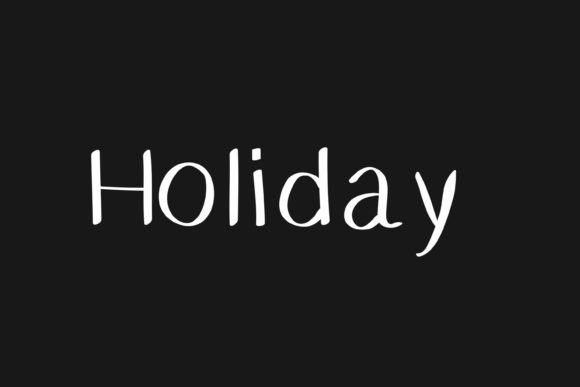
Holiday Font
適切なデザイン要素を見つけるのは難しい場合がありますが、Holiday Fontは作品を即座に引き立てる優れたコレクションを提供します。
POD(オンデマンド印刷)製品、結婚式の招待状、またはソーシャルメディアのグラフィックを作成している場合でも、Holiday Fontは理想的です。